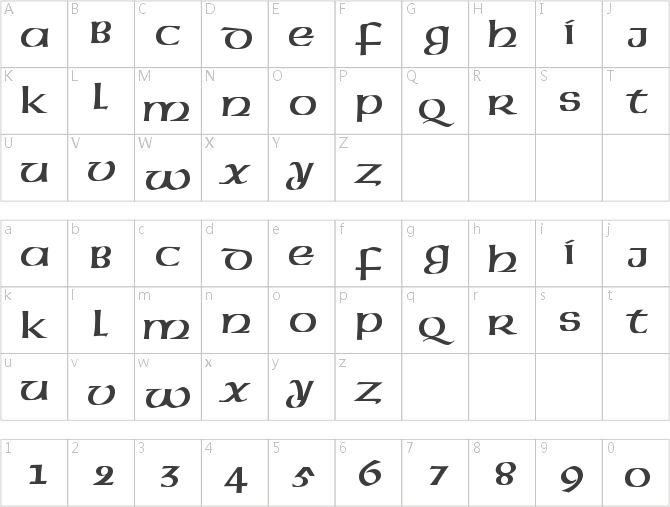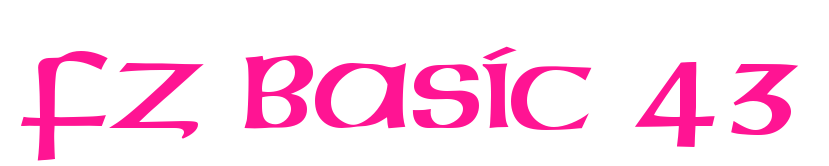
FZ BASIC 43 詳情頁(yè)
FZ BASIC 43字體字庫(kù)是一款讓人賞心悅目、百看不厭的英文字體,適合各類(lèi)廣告和產(chǎn)品包裝設(shè)計(jì)應(yīng)用,字體大小0.06MB,格式為ttf字體,上傳用戶(hù)是昊天金誠(chéng),作者/版權(quán)方為未知